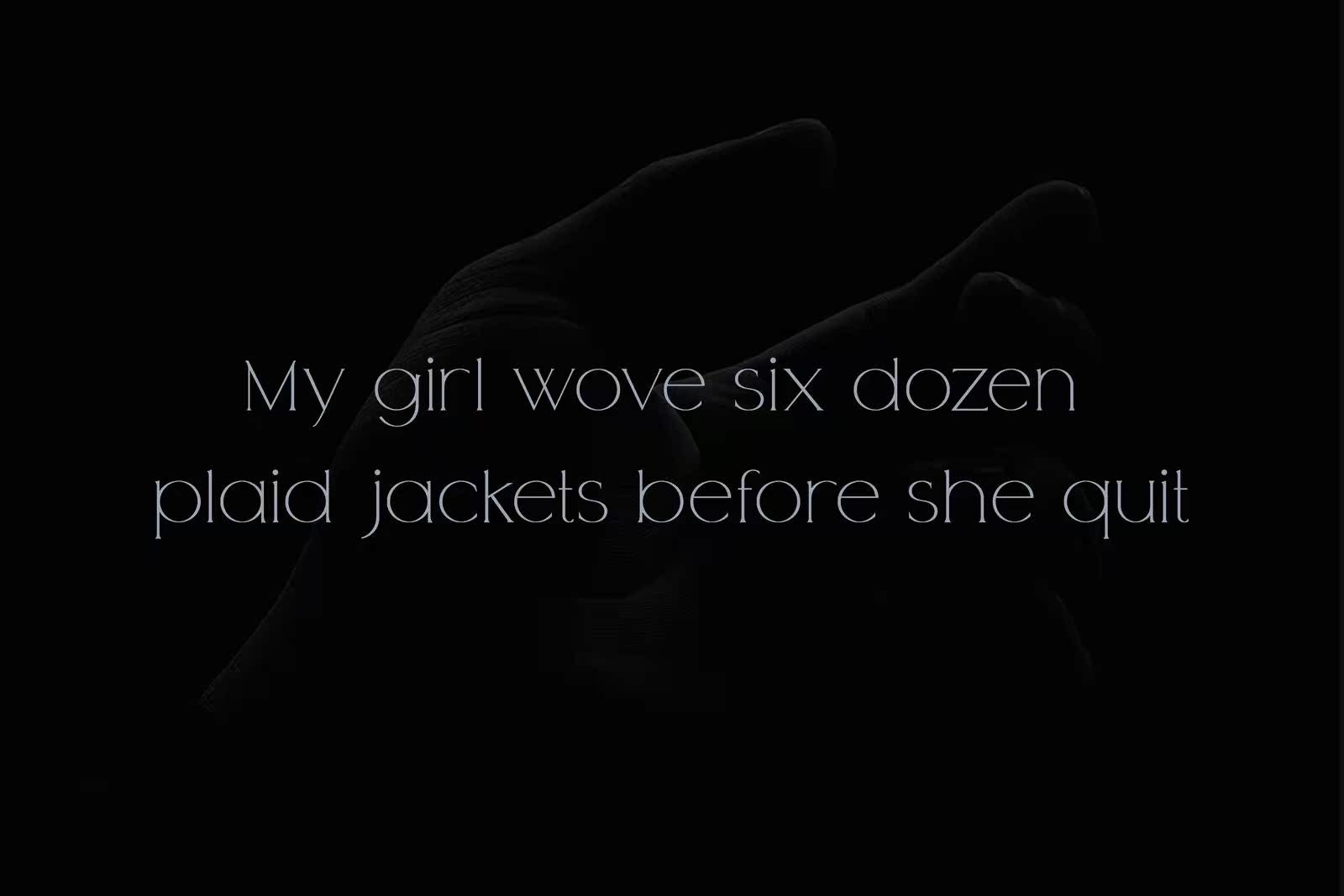
ZoelaisaStyleishSeriefDisplayFont。它是常规样式,包括多语种、连字、交替输入、数字和标点符号。您可以为项目创建自定义排版,如杂志封面和标题。ZoelaisaStyleishSeriefDisplayFont。它是常规样式,包括多语种、连字、交替输入,数字和标点符号。您可以为项目创建自定义字体,如MagazineCoversandTitles。